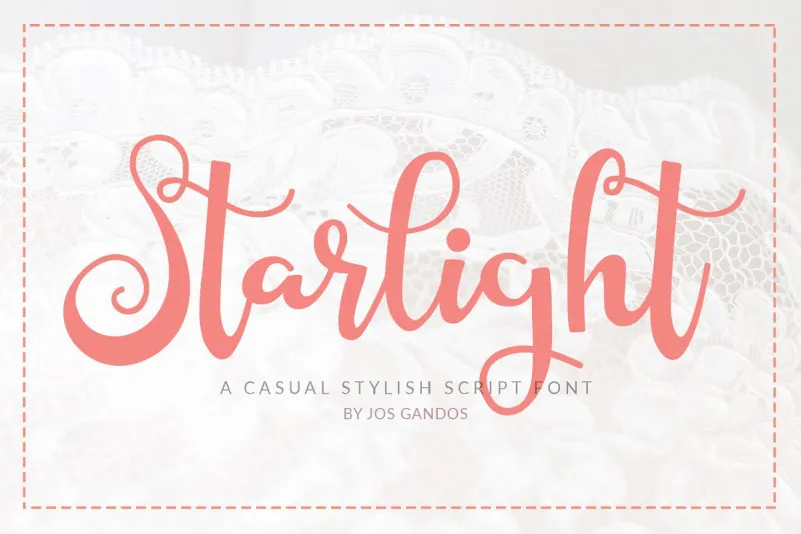
Starlight Script Font – Download Grátis
Olá amantes de Fontes! Aproveite a introdução à nossa nova fonte chamada Starlight Script Style. Este é um script casual e moderno, com uma pegada natural que adicionará elegância ao seu design. Starlight Script Style foi criado por jos gandos, oferecendo um estilo fresco de calligrafia que se destaca. Perfeito para projetos diversos como fotografias, marcadores, designs de citações, postagens no social, panfletos, logotipos e marca, convites, desenhos de produtos, rótulos, assentamentos, designs de casamento e embalagens de produtos, até mesmo eventos especiais ou qualquer projeto que precisa de uma pitada de escrever a mão ou simplesmente um design elegante com texto estilizado sobre fundo. Seja você um designer profissional ou iniciante, Starlight Script Style é uma fonte perfeita para tornar seus trabalhos únicos e sofisticados. Não deixe de experimentá-la! Você pode inserir o nome que desejar abaixo, para começar a desfrutar desta nova opção de estilo elegante e fresco no seu próximo projeto.